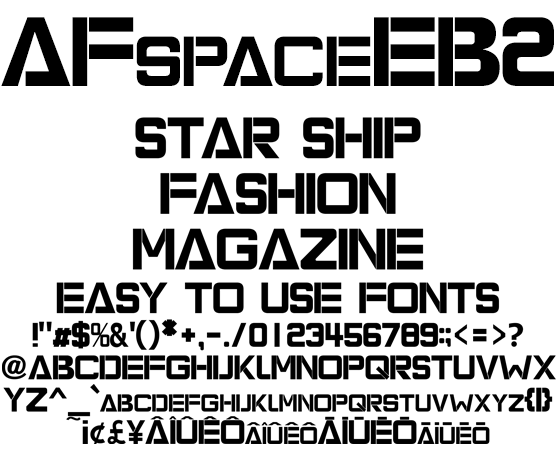
特大見出し専用欧文フォント AFspaceEB2
AFspaceEB2
AFspaceEB のデザインを変更し見だし専用に特化しました。小文字は大文字デザインのスモールキャップス、未来感あるキャッチな場面でご利用ください。同人系、コミック、アニメ、ゲームに最適。パンフレット、リーフレット、フライヤー、ファッション系コンテンツに使えるフォントです。日本のローマ字表記で使われる訓令式やヘボン式で扱う Ô や Ō を収録、人名地名へのアプローチもリアルです。